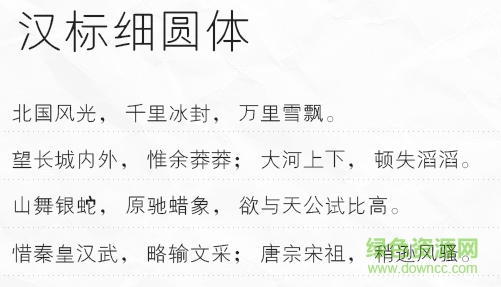
漢標(biāo)細(xì)圓體
漢標(biāo)細(xì)圓體字體是一款圓潤優(yōu)美的漢標(biāo)字體,結(jié)構(gòu)方正飽滿,線條流暢,可應(yīng)用于各種排版設(shè)計(jì)中,綠色資源網(wǎng)匯聚更多高品質(zhì)的ttg字體,需要的朋友快來體驗(yàn)吧!
漢標(biāo)細(xì)圓體特點(diǎn)
字體風(fēng)格舒展柔和,筆畫纖柔,適用于女性、兒童和生活用品類的宣傳冊和包裝設(shè)計(jì)等,也適用于正文排版!